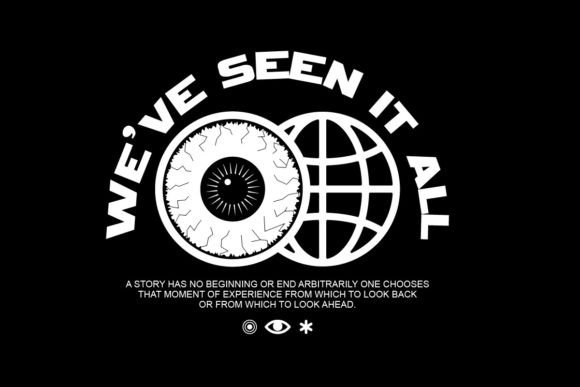
Weve Seen It All Graphic Design
Việc tìm kiếm các thành phần thiết kế phù hợp có thể là một thách thức, nhưng Weve Seen It All Graphic Design cung cấp một bộ sưu tập đặc biệt giúp nâng tầm công việc của bạn ngay lập tức.
Được chế tác với độ chính xác cao, Weve Seen It All Graphic Design cung cấp các vector sạch, kiểu chữ mượt mà và giấy phép thương mại để bạn yên tâm.